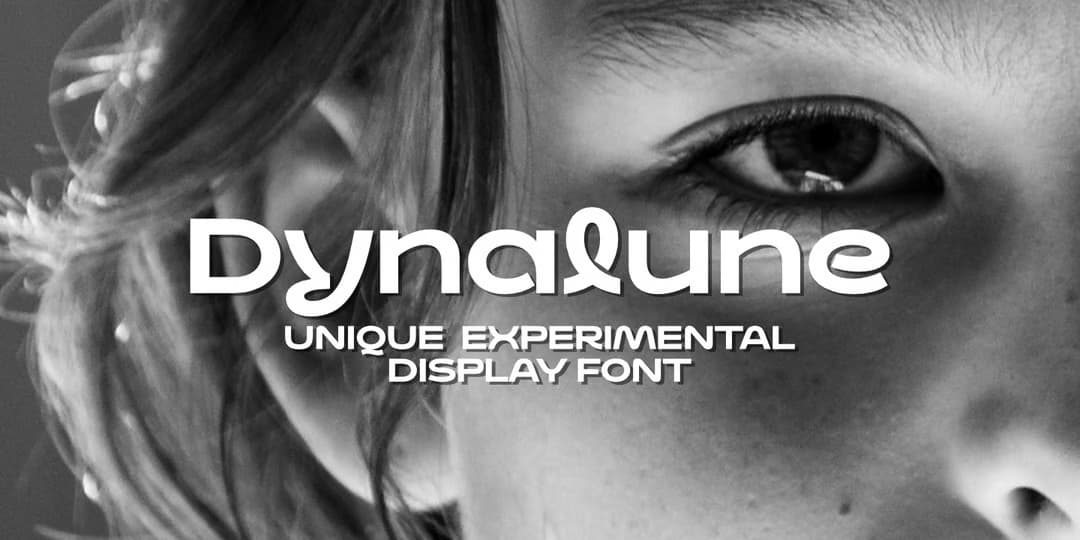
Dynalune
ユニークでポップなグリフながらクールな雰囲気のサンセリフディスプレイ。カーブしたストロークが特徴で、特に小文字は手書きのようなニュアンスが強く出ているが、ストロークが太めで抑揚がなく、やや幅広のプロポーションとかなり大きいxハイトで、雰囲気はあくまでモダンでクール。あまり見ない個性的な書体である。リガチャーが少しある程度でオルタネートなどはないが、そのまま組んで十分目を引くだろう。1ウェイトのみ。